学习组:由文字设计为起点的思想沙龙
位于杭州的「学习组」是一个以视觉研究、设计考古、活动分享、展览及写作出版为目的的小型思想沙龙。过去七年,它始终保持在一个不喧哗的小范围里运作:以文字设计(Typography)为起点,不断伸向更宽的知识与生活领域。几位成员多有写作、设计、策划等多重身份。大家在「求同存异」,各有研究方向与兴趣偏好的同时,还能在同一主题下拿出真材料、真问题,彼此激发。郦亭亭说:「不装,主打一个随遇而安。」这也是学习组的气质。
小组日常活动有读书、看展、分享会,也有烧烤、郊游、live 演出。谁发现了有趣的展览、书或物件,很少私藏,往往一叫就是一桌人。许多严肃话题,其实是在这种松散的闲聊中定下来的。时间和场地都不固定,从工作室到苍蝇馆,临时起意的相聚并不少见。他们也频繁邀请不同领域的朋友来做「跨学科外援」,用以「避免知识固化和窄化」。从庄子哲学到 Audio-Visual 艺术,从杭州街巷到瑞士圣加仑(St Gallen),小规模、面对面的知识交换,不断越过地域与学科的边界。
学习组七周年之际,以下为几位成员的活动现场分享内容整合,虽无法全面展现学习组风貌,但也借此为这个「神秘组织」掀开一角。
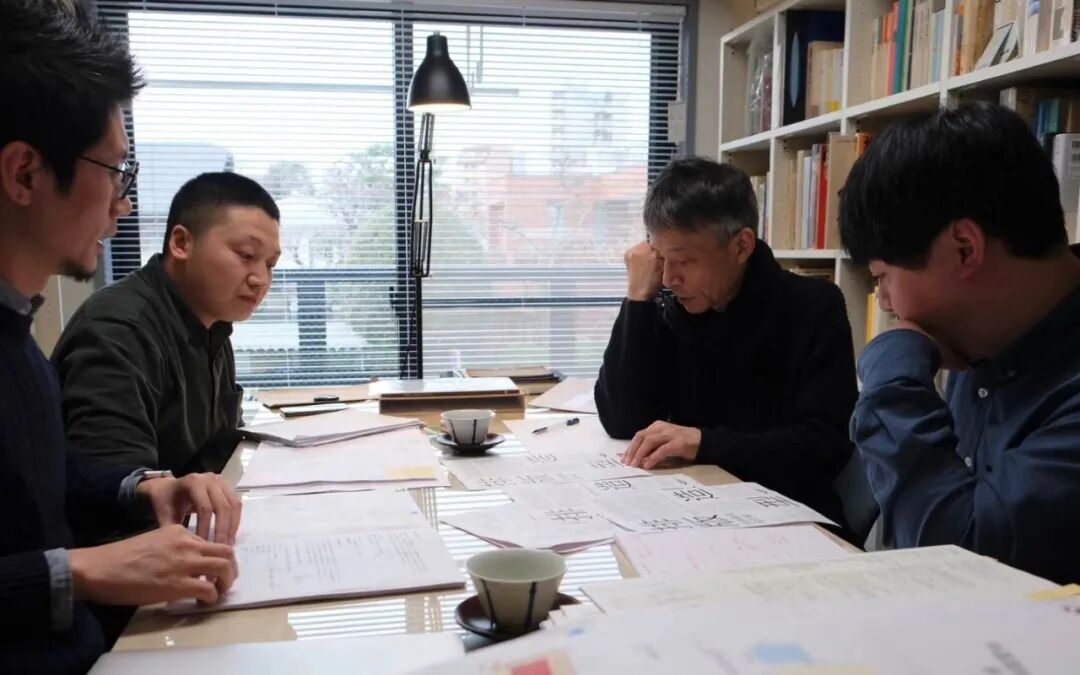
2020 年拜访白井敬尚先生,探讨《排版造型》中文版出版与展览项目
开放式学习的松散与集中
学习组成员们的成长背景、专业路径差异很大:有人偏出版与字体,有人以展览与图像研究为主,有人深耕教学与公共视觉,有人专注字体与工具开发。在这种差异下,几位核心成员很早就已经通过多重项目有了交集和合作:他们在虞琼洁主理的「白说」系列活动中轮番做嘉宾,也在纸张品牌的「纸约设计师」企划中合作。再往前,还一起筹备过中岛英树展、白井敬尚展等项目,大家交流逐渐深入,为学习组的诞生埋下伏笔。
邵年回忆 2017 年筹备中岛英树展时,与赵宛青、虞琼洁(小白)、卢涛一起工作的经历——策展本身就是一场「被迫集体深度学习」。展览结束后,这种在项目里自然发生的学习氛围,顺势被延续成了更长期的学习组。赵宛青笑称自己「顶多是编外」,但她也点名了两位核心人物的作用:一位是「半个老师」的卢涛,负责把大家「揪到一起」并推着往前做知识输出;另一位则是慷慨地长期提供场地与资源的虞琼洁。
2018 年 7 月 1 日,非白工作室举办了一场「学习日」,这一天后来被定为学习组的正式生日。
对于「学习组」的独特性,卢涛将其阐释为「凝聚之后又打散」:缘分是相伴的起点,但更重要的是,组内始终保有批评与自我批评的氛围,且这份交流能自然融入舒坦的日常。方宏章则直白地将团体定义为「知识交流站」,认为它恰好能应对当下知识碎片化、认知片面化与专业孤独感的困境 —— 正是每个人的差异与共性,让大家愿意主动凑在一起。如郦亭亭所说:即便成员各有专属兴趣与研究方向,但围绕既定主题展开讨论时,总能沉下心钻研、相互激发,始终保持「不装、随遇而安」的松弛姿态。
在这种状态下,学习组以广义「Typography」(文字设计 / 字体排印)为核心,研究范畴覆盖历史考古、设计思考、文本阅读、展览策划、设计写作、设计八卦、内容图谱等等。日常交流不拘形式且不定期开展:有时是共同观展后围绕展陈内容交换想法;有时是组员结合近期学习心得、特定事件或现象提出议题;有时众人携带相关资料与书籍参与讨论 —— 这类讨论侧重学习与思想碰撞,不刻意追求定义与结论。
设计研究的不同面向
卢涛:在二十一世纪重新思考「新文化运动」
卢涛是设计师、研究者,也是长期的视觉写作者。一方面涉足从主流商业包装到亚文化的视觉经营及推广,又秉承视觉写作精神,打通传播与设计、评论及出版的界限。最近研究起了中国近代史,以及与当今 AI 崛起、文科没落时代的关系:「以前西方的看多了有点腻,然后终究西学为用,我们该嫁接到怎样的本体上呢?」在他看来,如今各种线上线下开幕式上中西人士济济一堂,并不自动等于「天下一家」,很多时候只是客气地互相致意,缺乏真正触及结构性问题的对话,这种「中西合璧」的想象有点天真。
这些年他的阅读兴趣逐渐从设计圈内转向文史哲的漫游,直到发现「五四」与「新文化运动」可以作为一个有效切口:一方面,中与西、新与旧、「德先生」与「赛先生」这些争论在今天仍在同一条延长线上,所以他在学习组七周年的题图上写下「东方在西方的哪一边?谁的现代?青年早死,所以新鲜」作为问题核心;另一方面,那一时期涌现的人物几乎是近代一百年的「时代之选」,他们的遭遇与纷争为我们重返历史现场、重新分析提供了极好素材。对比之下,当下设计界却是辉格史观的重灾区,「除了奖项和大客户为唯二导向之外就没有任何导向了」,在这套价值观下,学习组里许多围绕文史哲的讨论,在主流看来几乎是「没有意义的」。但卢涛的判断很冷静:「文科本身不会没落,没落的是 PPT 快手们。」
学习组 7 周年活动现场卢涛现场写「玻璃板书」
郦亭亭:「把书读厚」到「厚书薄读」
郦亭亭作为独立设计研究、写作与批评者,将自己的方法概括为从「把书读厚」走到「厚书薄读」。她长期追溯现代主义百年来围绕「设计是什么」的不同思考,从大量文献里筛选出设计与观念先锋的宣言,从最初25位计划扩展为50 到100 位。之所以走上这条路,与她早期实践局限于形式化视觉有关,当开始参与城市形象等复合型项目时,遭遇到因知识结构不足的专业瓶颈。于是赴香港理工求学,被导师 John Heskett 以一句「What is Design? Design is…?」直接击中,促使她开始认识到,设计价值的变迁来自经济、社会与政策结构等动因,也意识到以往设计教育存在重技巧而轻系统与观念等根本问题。随后她又补上一门哲学课,从另一个维度重新理解「设计可以作为什么」,在密集阅读下逐步完成了「把书读厚」。
真正的转折发生在她从事设计教学之后。她发现「把书读厚」只是起点,更重要的是能否「读薄」,即能否把知识消化再提炼,进而清晰、可传授、可传播的方式重新表达。十年前她回到杭州并加入了学习组,在共学主题Typography 中从杂学走向精研,逐步建立自己的研究体系。她强调,如果不了解构成主义、包豪斯到乌尔姆的教育演变,也不了解二战前后的社会转型,就无法真正理解莫霍利–纳吉(Laszlo Moholy Nagy)被无数人引用的那句「设计不是职业,而是态度」在今天更多元的知识生态里,「厚书薄读」更具现实意义:人类的任务不是制造更多信息,而是从既有知识中提炼能激发创造力的新知。在 AI 时代突围,需要如何向历史质问、向未来设问的能力。
张弥迪:为设计而阅读
张弥迪是平面设计师,杭州聿书堂创始人,长期专注书籍设计与字体排印。他对计算机时代之前的印刷物格外着迷,并收藏大量国内外藏品;这些实体书既是他学习的材料,也是他构建「为设计而阅读」方法论的起点。大学时,他便决定走向字体排印与书籍方向,这与他自幼练书法、对文字的敏感有关。真正改变他视野的,是接触前计算机时代的印刷体系——铅印时代的作品质量扎实,许多看似过时的《排版手册》其实是前辈总结出的经验结晶;相较之下,电脑普及初期的设计行业因缺乏手绘基础,加之滥用特效,反而催生大量粗糙、单一的排版风格。手绘美术字的自由与生动,也在那段历史中留下难以复制的多样性,让他意识到技术限制反而塑造了更高的底线。正是这些观察让他将研究重心转向「前计算机时代」的排印体系,把它视为理解当代设计问题的钥匙。
在向前辈学习的过程中,他策划了「现代字体排印研究系列」出版与展览计划,例如将白井敬尚的《排版造型》系统梳理,为此尽力搜集其相关作品、出版物与资料,以便同时分析设计方法与整体气息,训练自己的视觉判断。他也在这一过程中形成了自己的阅读方法,即「为设计而阅读」。他认为以自己为例的设计师们常只「看」书不「读」书,而真正的理解需要深读和思考。他引用梁启超的「抄读法」,认为这种看似笨拙的方法能让知识真正进入身体。于是他把读来的句子抄写下来,以此加深理解、训练书写,这些「设计抄读」也逐渐积累成册:《为设计而阅读》,灵感来自诺曼·波特(Norman Porter)的同名文章。对张弥迪来说,这既是一种学习方式,也是一种持续反思的实践。
童亦:让字体成为思考的容器
童亦是平面设计工作室 Quinsay design 的艺术指导,并在 2020 年创立 Quinsay Type。他长期专注字体设计,这份专注既来自个人兴趣,也来自实践需求。最初促使他投入字体领域的契机并不浪漫:在调试字母曲线时,他意外发现这种工作与工业产品的线条优化有着某种结构性的相似,这种「形的逻辑」让他意识到字体不仅是造型,更是一种可被思考的系统。随着他在平面设计领域的深入,他越来越清楚语言文字对于视觉文化的基础性意义,因而开始持续设计字体,并将其贯穿于自己的项目之中。
在他的方法论里,字体是「思考的容器」。他围绕「形式」「结构」「气质」三个维度展开探索,不同历史阶段的视觉语言、文学意象,乃至生活中的朴素观察都可以成为字母形态的生成动力;有时字体甚至具备某种自我叙事的能力。他同样关注中西文字体系之间的转换问题:设计师在处理非母语文字时往往带着「方言式的语气」,这在日本尤其明显——汉字与假名并存的背景,使得日本设计师在处理西文字体时形成了区别于欧美的独特方式。基于这种观察,他在设计西文字体家族 Cinah 时试图让字母带有「东方语气」:一方面回溯部分字母的早期形态,另一方面在西文字母惯用的切口之上,引入隶书出锋提笔的劲力,以末端竖切与曲直转换的线条,传递汉字书写的流动与力量。他希望这个字体家族不仅能够自然呈现东方视觉思维的延伸,同时能够更好的与中文黑体字适配。
邵年:模糊平面与书籍设计的边界
邵年是平面设计师,现为「公共劳动」(Public Labour)创始人。他在书籍、杂志与视觉系统之间长期游走,也因此对「平面设计师」与「书籍设计师」的界线有自己的一套判断。最初,他认为书籍设计的核心特质在于其「不可逆」:书一旦出版,就不再像海报、网页或品牌视觉那样可以随时调整,它具有恒定性,也不依赖时效性,这让它在设计领域里显得独特。
但随着经验累积,他的看法发生了转变。如今在他的日常实践中,平面设计与书籍设计往往并行发生,两者本质上都是「以语言为事物塑形」的过程,而不是截然不同的类别。在做书时,他很少在起点就把所有结构想清楚,也不以严格的流程推进,更多是「一边做,一边生成」;这种状态与他在做平面设计时的即兴性反而更接近。也因此,他倾向模糊两者的界限,让设计在更自由的空间里展开。「对我来说,它们的不同与相同一样多」,他这样总结。
转化经验与推动社群
方宏章:设计师应该具有社会性
方宏章是平面设计师,同时在浙江工业大学任教并活跃于策展实践。他长期关注公共视觉系统,对国内设计竞赛与公共设计生态中的「官本主义」现象有相当敏锐的观察。在他看来,过去几年里,工作室承接的一些公共视觉项目让他更直观地看到所谓「中国特色视觉奇观」是如何形成的。一方面,随着更多公共视觉设计进入大众视野,它直接参与社会建构,也塑造着公民的审美与认知;自媒体舆论的兴起又反向逼迫政府部门调整决策,这使得某些方面已有明显改善。
但另一方面,公共视觉领域依然充斥大量质量低劣的「视觉垃圾」,背后是评选体系的滞后与专业标准的模糊。对照国外情况,公共设计真正走入现代意义上的公众生活也不过是七八十年代的事,其成熟依赖政府、设计群体与公众的共同作用。方宏章认为,中国的公共视觉生态同样需要更多专业设计师投入其中,以推动结构性改良。在他眼中,设计始终是一种社会性实践;只有承担社会性,公共视觉中才可能同时容纳秩序与诗意。
学习组七周年活动现场
虞琼洁:设计师的多重身份
虞琼洁身兼数职:既是中国美术学院视觉传播学院副教授,也是非白工作室创始人兼艺术指导,同时运营着 Transtage 转场这一独立展览空间。她在这些身份之间切换自如,但不是依靠「分身」,而是通过长期摸索出一套自己的学习与实践模型。
她从 2011 年进入高校教学,同年创立 Transwhite Studio;2015 年设立替代空间 Transtage,并在 2021 年搬迁后把它真正发展成独立面向公众的展览平台。多重身份对她而言不是负担,而是互相牵动的结构。她认为设计实践容易陷入固定范式,流程化会带来疲惫,因此必须保持一种「随时归零」的警觉状态。教学为她提供反思与拓展的机会,让她不断在知识结构上「温故知新」;而策划展览则是一条向外求学的路径,使她能主动接触新的议题、作品与方法,再反哺课堂与设计实践。最终,她将设计、展览、教学三者构建成一个自我循环的学习闭环,使多重身份不再分散,而形成持续生长的动力。
赵宛青 & 郦亭亭:设计中的女性
赵宛青是平面设计师,前 XYZ Lab 联合创始人,如今独立运营个人工作室 still growing,涉猎品牌形象、书籍、展览视觉,也参与出版物与展览的策划与传播。谈到设计师的性别身份,她的态度直接而清晰:设计成果有时会被读出「女性色彩」,但那不是必然,更不可能成为设计的出发点。她认为性别不应成为创作中的前置框架,也不需要被不断审视——女性占人类的一半,女性视角本身就是人类视角。真正决定作品差异的,是个人经验、思维结构、教育路径与审美习惯,这些差异远远大于性别差异。她也反问:若把同样的问题抛给男性设计师,他们是否会意识到性别在工作中有什么决定性作用?
郦亭亭从另一条路径补充了「女性身份」的复杂性。她坦言,行业规则容易在十年左右消耗一个人的创造力,让人陷入身份认同的停滞;她自己的破局方式是读书与研究——寻找前辈与同代的路径,判断哪些规则应该被打破。她认为最理想的研究是带有委托费用的,但没有的话也可以自建命题、自费研究,这是学习组「保持独立与持续」的重要共识。她特别提到虞琼洁:十余年来以展览空间与工作室的双重结构持续做研究、策展、办展,同时承担教学与母职,是一种难得的持续性力量。七年间,她在学习组遇到多位类似的女性设计师——不执着于外界的定义,不为性别框住自己,保持学习、储能、蓄势,再不断向前。
自然生长未来可期
七年下来,学习组始终像一株按自己节奏生长的植物。它不追求囫囵吞枣,也不执着于学术化的严整框架,而是把知识与日常混在一起,以缓慢而稳定的方式吸收、发散。没有宏大的规划,也没有必须完成的指标;有的是一种以独立为底色的松弛节律,让讨论自然生长、在不同领域之间自如穿行。思想的碰撞不以结论为目的,而在持续的往返中生成情谊与判断力。
卢涛说,「继续健康开心地活着」;方宏章说,「随机生成」。这两句话恰好概括了学习组七年来的状态:不紧、不迫、不装,靠的是一群人共享的耐性与好奇心。未来,它大概仍会像这样延续自身的步调,在知识与友情之间缓缓扩展,稳稳地生长下去。
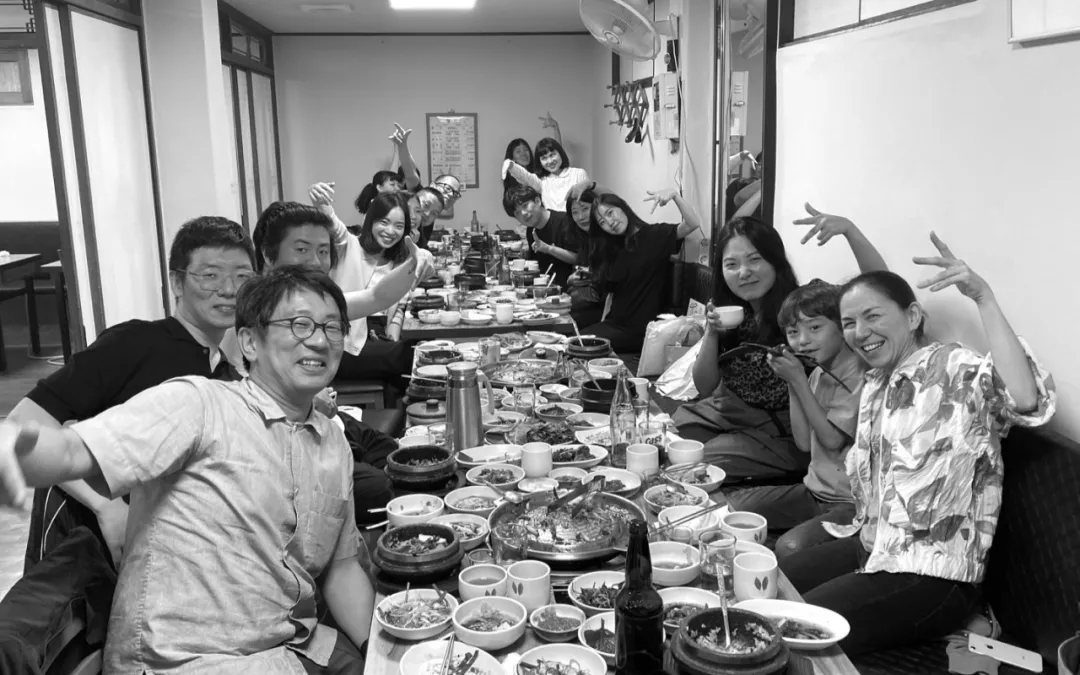
2019 年学习组参加 typojanchi 韩国国际字体双年展